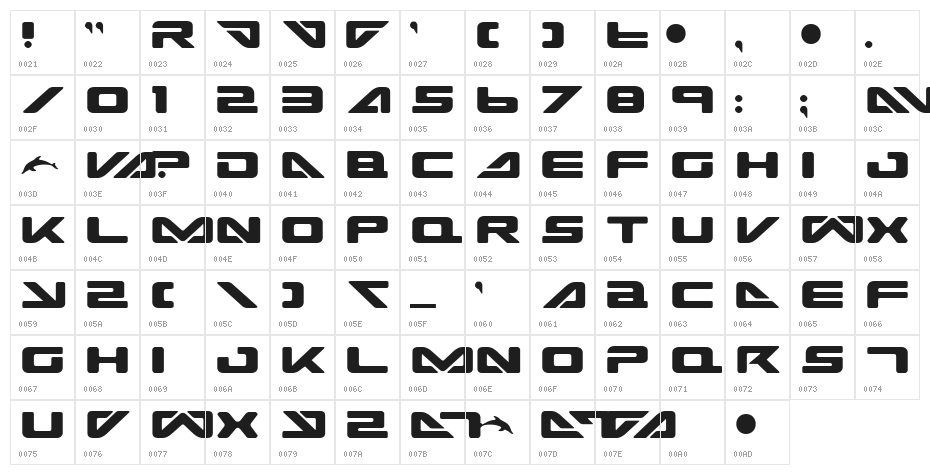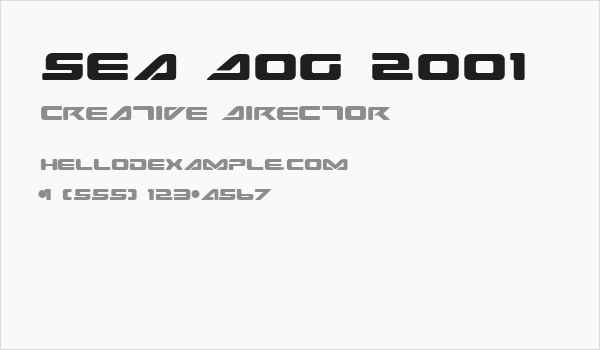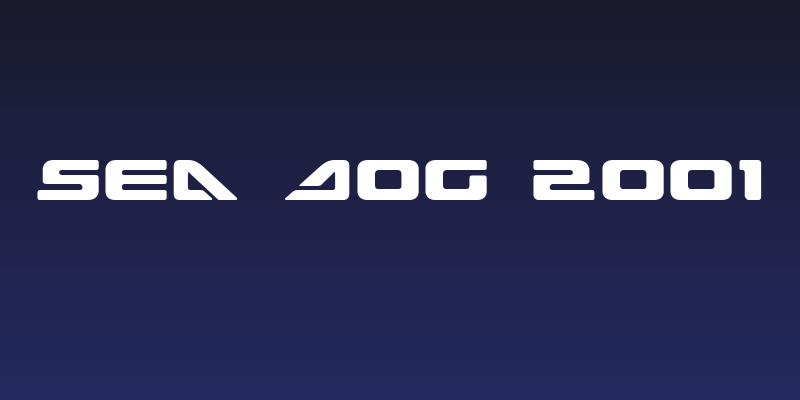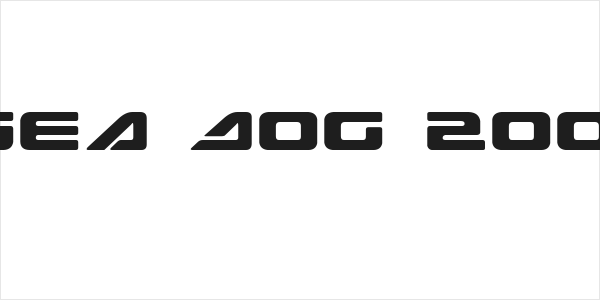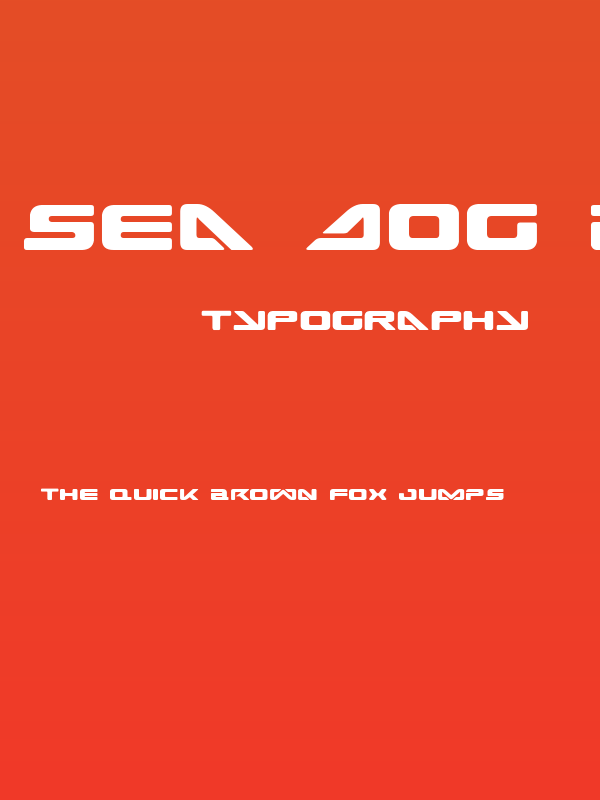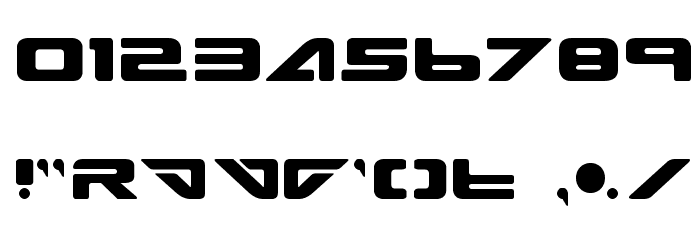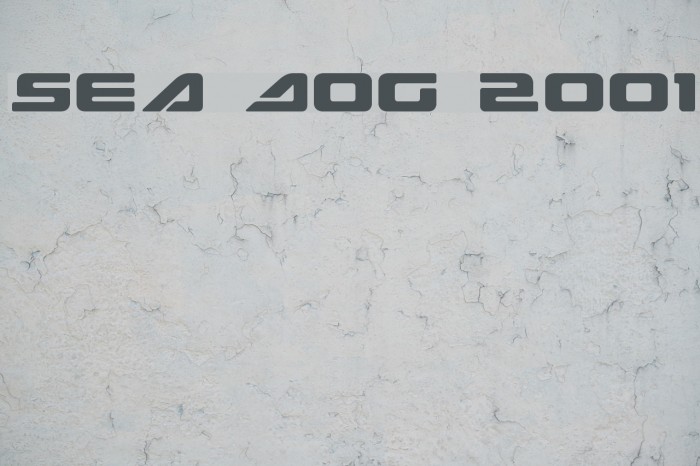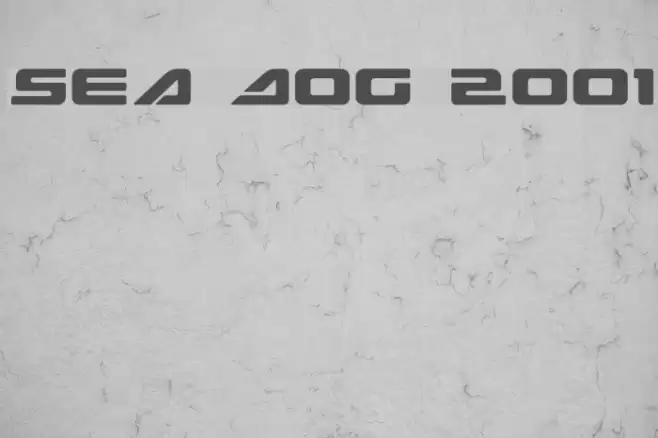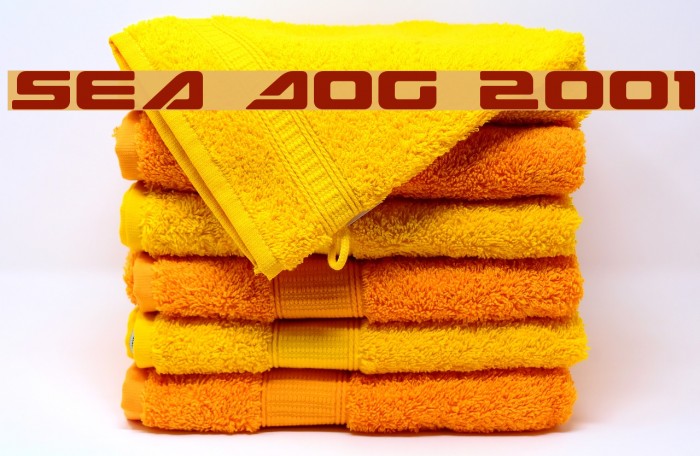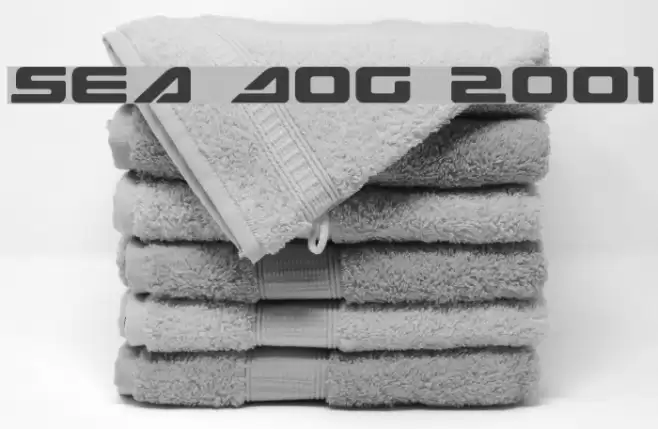
Sea Dog 2001 Font
Fonts by Iconian Fonts - Daniel Zadorozny
| Caso d'uso | Logos, Headlines, Display text |
| Progetti proposti | Ideal for technology branding, sci-fi themes, modern digital interfaces, and edgy graphic designs. |